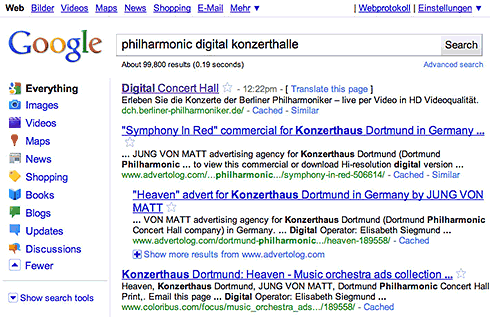
Frischzellenkur bei der Google-Suche und beim Google-Logo: In Deutschland und vielen weiteren Ländern sehen die Besucher seit heute eine ziemlich neue Suchergebnisseite. In einer linken Spalte erscheinen jetzt die mit farbigen Icons markierten Suchoptionen und Inhaltstypen des Internet-Giganten, von der Bilder- und der News-Suche über die (in Deutschland noch umstrittene) Durchsuchung von Büchern bis hin zu Blogs und Diskussionsseiten. Damit stehen erstmals alle Suchoptionen zentral an einer Stelle zur Verfügung. Die Reihenfolge der Optionen ändert sich dynamisch, je nachdem, welche Suchen man anstößt. Ist diese beispielsweise mit üppigen Fotoergebnissen verknüpft, wandert die Rubrik »Bilder« an Position 1 der Liste.
Darüber hinaus kann man ab sofort Ergebnisse für einen bestimmten Datumsbereich anzeigen lassen, und die besten Ergebnisse mit Sternchen bewerten, um diese bei der nächsten Suche schneller wiederzufinden. Weitere Schalter erlauben die Sortierung nach Aktualität oder starten eine Suche nach verwandten Begriffen.
Auch das Google-Logo wurde renoviert, genauer: entschlackt. Mit dem Schlagschatten verschwand auch die übertriebene Plastizität der 6 Buchstaben, so dass die Farben jetzt reiner erstrahlen. Bemerkenswert für ein US-Markenlogo ist der Abschied vom Trademarkzeichen ™. Gerade bei Google ist das ein Signal, denn dem Konzern wird von Politik und Verbänden seit Monaten vorgeworfen, Urheber- und Persönlichkeitsrechte zu ignorieren. Wenn Google diese Rechte zum Allgemeingut erklärt und ins Zentrum seines Business’ rückt, kann die logische Folge daraus nur sein, den Schutz der eigenen Identität – zumindest optisch – zurück zu fahren. Neues Motto: Das Google-Logo ist für alle da?
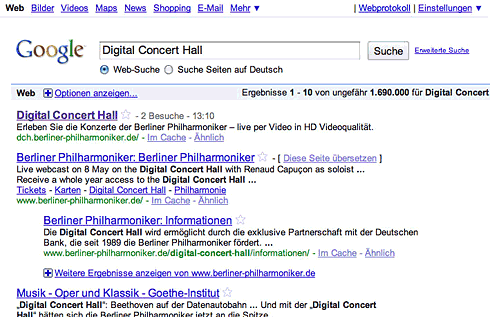
Wie Google noch bis gestern aussah, zeigt die Abbildung unten. Der Originalpost von Marissa Mayer, Googles Vizepräsidentin Search Products & User Experience, ist auf dem offiziellen englischen Google Blog zu finden.
Das ‘™’ (Trademark)Zeichen steht im Englischen ja lediglich für das Vorhaben oder eine provisorische Markenanmeldung. (Im Gegensatz zu ‘®’ / Registered Trademark — Also einem registrierten Markenzeichen.)
Und wenn das englische Copyright auch nur ansatzweise dem österreichischen (und dem deutschen wahrscheinlich ja ebenso) Urheber-/Markenrecht ähnlich wäre, könnte mittlerweile die Marke (und das Logo von) ‘Google’ auch solche Bekanntheit erreicht haben (Gebrauchs-/Verkehrswert), dass auf die zusätzliche Angabe (™/® oder Artverwandtes) verzichtet werden kann/könnte. (Und wäre damit dennoch weiterhin rechtlich geschützt.)
Also ich sehe (unangemeldet) bereits die neue Variante vor mir. (Könnte aber natürlich auch an der Verwendung von Chrome als Browser liegen.)
Ok, dann liegt’s an der Sprache, obwohl ich das System auf englisch eingestellt habe öffnet Safari Google Deutschland. International ist die neue, lokal die alte Version zu sehen. (.com/.de)
bzw. die Sprache bleibt gleich, nur die Top-Level-Domain lässt sich umschalten und das Layout wechselt mit…, Google erlaubt in Safari kein Englisch mehr für Deutsche mit englischem System.
Bei mir wird sowohl die .com-, als auch die .de-Seite noch im alten Stil angezeigt. Und auf der .co.uk-Seite gibt’s auch noch ein „Doodle“ in alter Gestaltung:
inzwischen bei mir beides neu… – eventuell provider-abhängig und cache leeren…
Hm, die Bewertung mit den Sternchen finde ich bei mir nicht
Und auch die Ergebnisseiten sehen komplett anders aus. Habe dazu mal ein paar Vergleiche gemacht, kann man sich hier ansehen, wenn man will.